さて、フォントの直立体を仕上げたところで、深刻なイタリック体への不安に直面しています。簡単な解決策は、オブリーク体です。しかし実際には、本物のイタリック体でさえ、大文字とスモールキャップは依然としてオブリークにする必要があります。あなたの文字の形を傾けるための最良の方法を、素早く見つけましょう。
オブリーク体を作成する良い第一歩は、Glyphsの標準インストールに付属する事前インストール済みのフィルタの一つ、「変形」フィルタです。結果は様々ですが、良いオブリーク体の角度は通常6度から12度の間のどこかです。
「パス > 変形」を選び、平行移動はせず(つまり、値をゼロのままにする)、拡大縮小もせず(100%のままにする)。しかし、「原点」は選んでください。ベストプラクティスとして、「xハイトの半分」を選ぶことをお勧めします。なぜなら、これはGlyphsがイタリック体のサイドベアリングを計算するためにも使用するからです。つまり、LSBとRSBの間で相互参照を持つメトリクスキーを使用できるということです。それが何を意味するかわからないですか?スペーシングのチュートリアルを覗いてみてください。
傾斜と筆記体化
次に、角度と、デザインをイタリック角度にするモードを選びます。「変形」フィルタは2つの可能性を提供します。最初のオプション「傾斜」は、お気に入りのベクターアプリケーションでよく知られている単純な幾何学的なせん断です。問題は、水平線は重さを保つのに対し、歪みによって垂直線の重さが失われることです。良くありません。
2番目のオプション「筆記体化」(「傾斜」という単語をクリックして「筆記体化」に切り替えます)は、カーブの歪みに対抗しようとします。比較はこちらです。
しかし、「Cursivy」はどうやって何をすべきかを知るのでしょうか?それは単に、カーブの補正を計算するためにあなたの標準ステムを利用するだけです。ですから、「ファイル > フォント情報 > マスター」(Cmd-I)で、適切な、平均的な水平および垂直ステムの値を入力するようにしてください。
プロのヒント
「ファイル > フォント情報 > マスター」に入力された標準ステムがカーブの補正を決定するため、異なるステム値を試すことで補正量を調整できます。あるいはもっと良いのは、カーシブ化されたバージョンを前景に、単に傾斜させたバージョンを背景に置き、その後「パス > 背景と補間」のスライダーを使って両者を補間することです。
これは、カウンターが過剰に補正されてとがりすぎているように見える場合に特に役立ちます。
極値点の修正
また、カーブ上のパスの極値の位置は、それに合わせて調整されません。これにより、垂直ヒントが不可能になり、補間やナッジングのような一部の操作が非常に難しくなります。もしヒンティングを気にせず、補間もしない、あるいはナッジングに頼らないなら、極値を気にする必要はありません。左のサンプルのようにパスをそのままにしておくことができます。
しかし、もし垂直ステムにヒントを付ける必要があり、補間を計画しているなら、右のサンプルのように極値を修正するのが良い考えです。「パス > 極値点を追加」を使うか、描画ツール(P)でカーブセグメントをShiftキーを押しながらクリックして、最も近い極値にノードを挿入できます。傾いた以前の極値を取り除くには、それらを一つずつ選択し、Deleteキーを押します。Glyphsはカーブセグメントをできるだけ良く再構築しようと最善を尽くしますが、「カーブをフィット」パレット(Cmd-Opt-P)で曲率をあちこち調整する必要があるかもしれません。
Toshi Omagari氏は、「Path > Delete Diagonal Nodes Between Extremes」というスクリプトを書いて、すべてのマスターで、一度にすべての斜めの極値を取り除こうとすることで、プロセスを高速化します。このスクリプトは、Toshi’s scriptsを「Window > Plugin Manager」からインストールすることで、他の多くのスクリプトと一緒にインストールできます。
直線のステムを修正する
しかし注意してください。「Cursivy」はボウルにはかなり良い仕事をしますが、直線のステムは単に傾斜されるだけです。しかし、角度が高くなるほど、あなたの傾斜による歪み、つまり垂直および右に傾いたステムが細くなり、左に傾いたステムが太くなるのがより極端になります。したがって、後でステムを少し調整する準備をしておいてください。例えば、垂直ステムを30度傾けると、約13パーセント細くなります。しかし、もしステムが以前は30度左に傾いていて、今や直立に傾けられると、そのステムの重さは16パーセントも増えます。
言うまでもなく、30度は非常に極端な角度です。この例では、ステムの歪みをより見やすくするためにそれを選びました。
傾斜の高さ
すでに上で述べたように、デフォルトでは、Glyphsはエックスハイトの半分を、メトリクスボックスを傾けるためのピボットとして使用します。この傾斜の高さより上では、ボックスは右に傾き、傾斜の高さより下では、左に傾きます。アイデアは、直立したテキストの間に傾いた単語(あるいはほんの数文字の傾いた文字)がある場合、両側にできるだけ少ししかはみ出さないようにすることです。通常、それは小文字のテキストになるので、エックスハイトの半分がピボットとして最善の推測になります。
しかし、時にはエックスハイトの半分が意味をなさないこともあります。例えば、オールキャップスのフォントを考えてみてください。その場合は、アプリのデフォルトを上書きする必要があります。これを行うには、「ファイル > フォント情報」を開き、「マスター」タブに切り替え、「メトリクス」セクションで新しいメトリクスを追加し、そのタイプとして「Slant Height」を選択します。
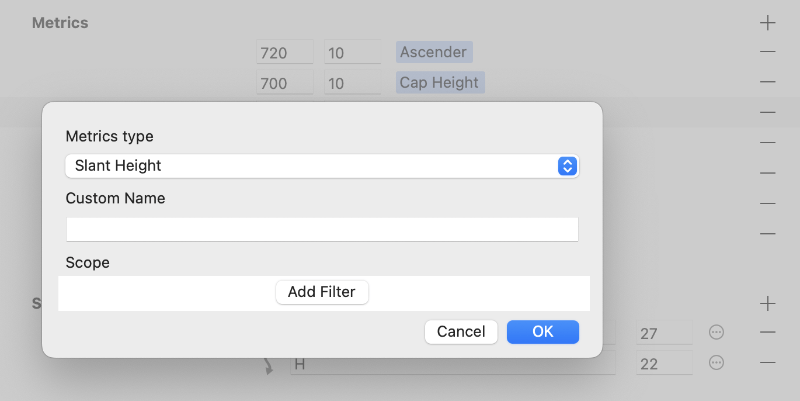
ダイアログを確認します。「マスター」タブに戻り、「Slant Height」を入力します。例えば、キャップハイトの半分などです。これで、少なくともこのマスターでは、すべてのサイドベアリングとメトリクスキーが、このピボットの高さを基準に計算されます。
便利なスクリプトとプラグイン
- Filter > Italic Extremes : 極値点を傾斜と直立の間で切り替えるためのプラグイン。
- View > Show Italic : もしローマン体とイタリック体が2つの異なるファイルにあり、同じファミリー名を共有している場合、ローマン体で対応するイタリック体のグリフを、その逆も表示するプラグイン。グリフの高さが同じかどうかも示します。
- View > Show Next Font : 上記と同様ですが、2番目のフォントが何であれ、それとです。
- mekkablue scriptsには、「Compare Frontmost Fonts」というサブメニューがあり、これはアップライトとイタリックの間のフォント情報、グリフセット、グリフの高さと幅などを比較するのに最適です。
- Daniel GamageとGuido Ferreyraのスクリプトコレクションには、ローマンフォントとイタリックフォントを比較・同期させるためのスクリプトが含まれています。